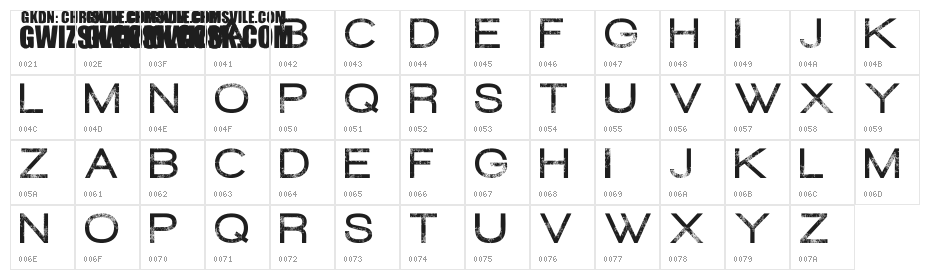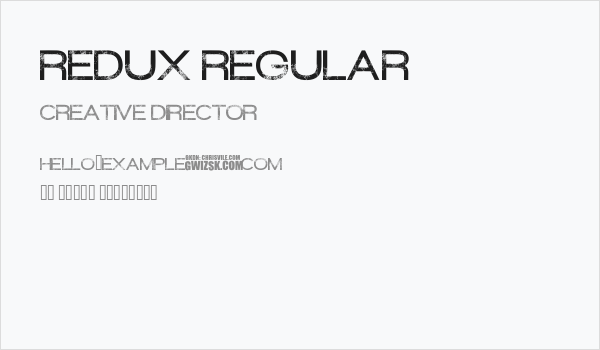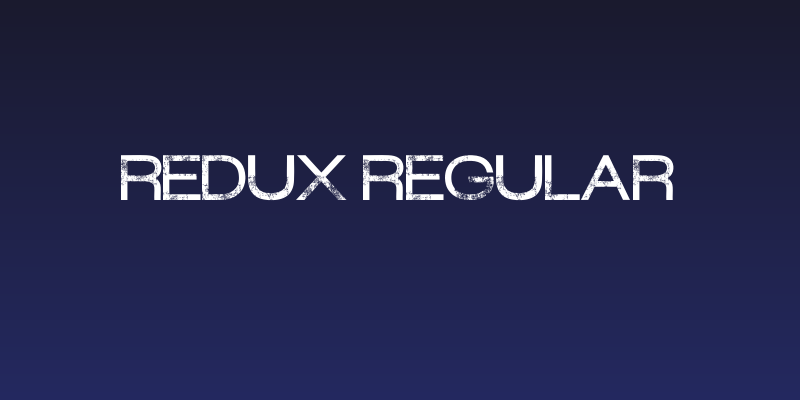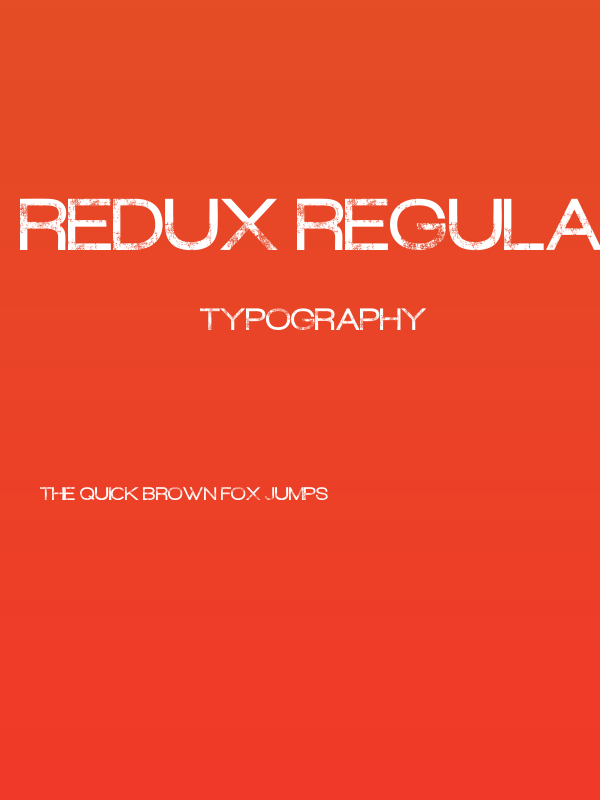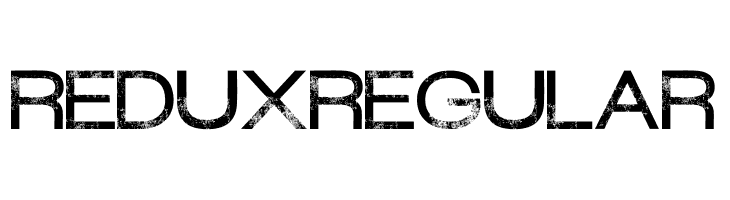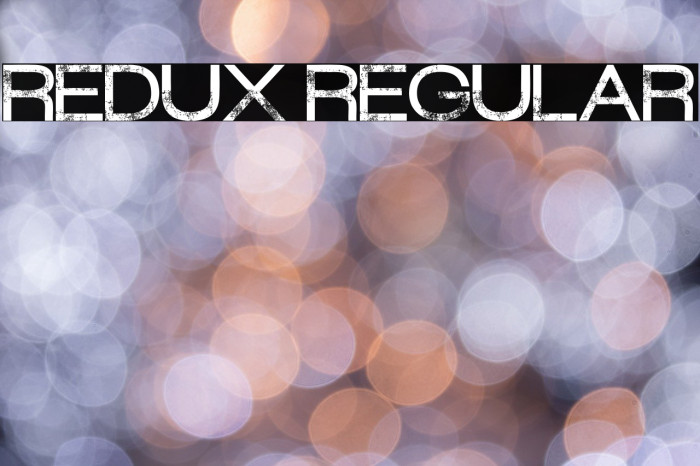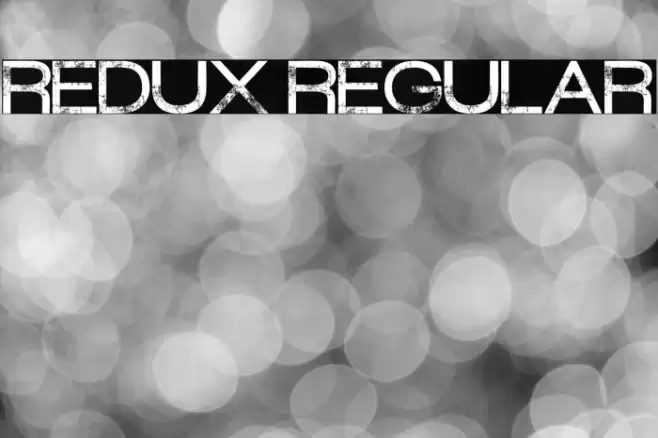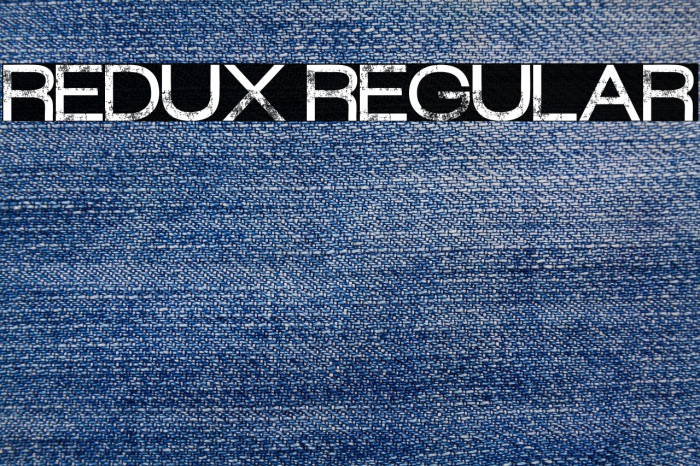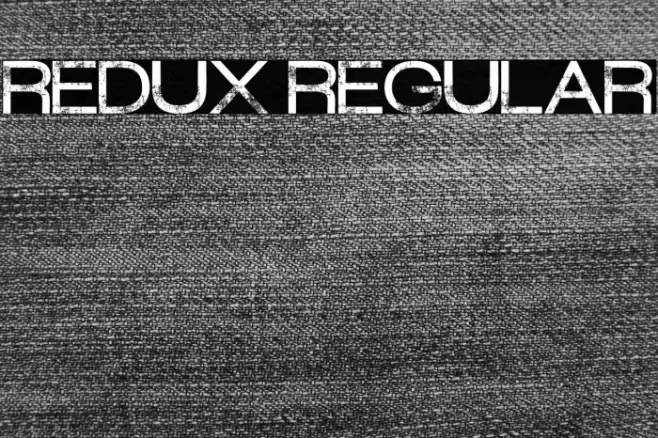
Redux Regular Font
✎ Distorted Eroded
| Gesamtstil | Vintage, Edgy |
| Vorgeschlagene Projekte | Ideal for album covers, posters, branding for edgy or vintage-themed products, and any design requiring a rugged aesthetic. |